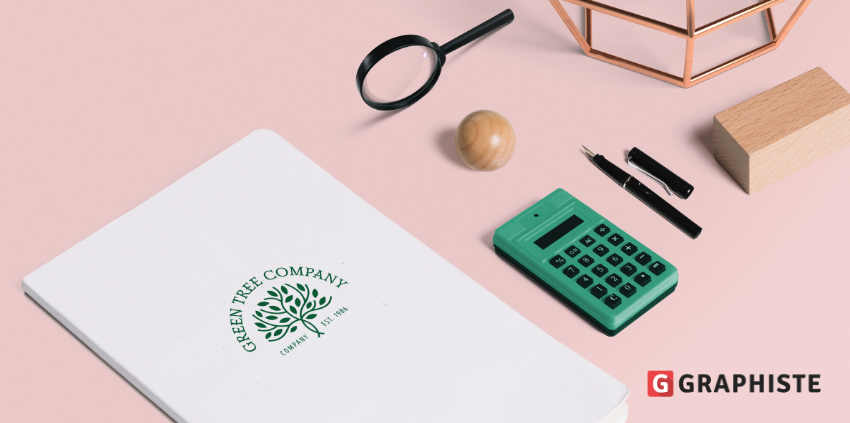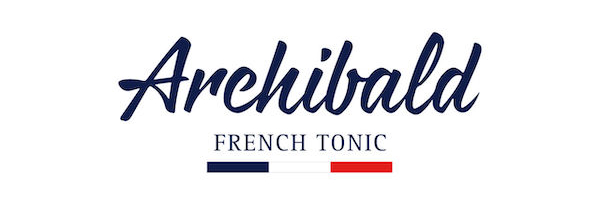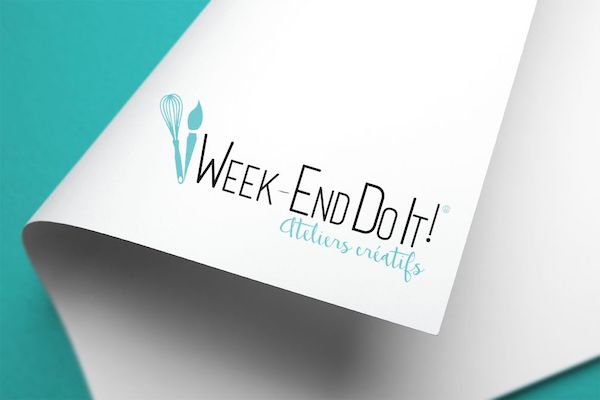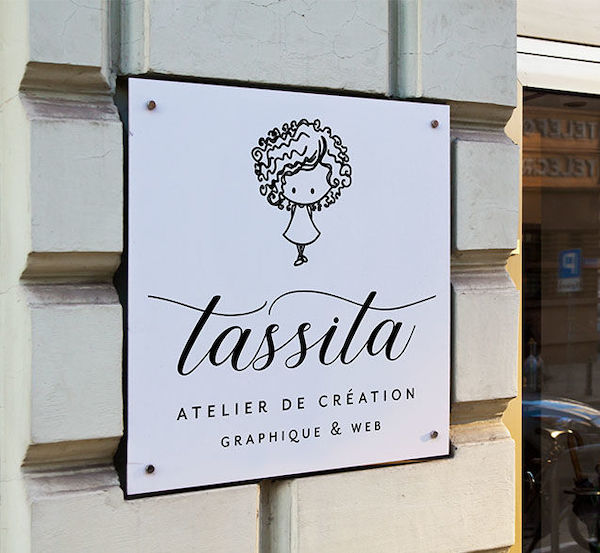
3 conseils pour choisir la typographie pour votre logo
Un logo, c’est une image. Mais c’est aussi une typographie. Que vous optiez pour le monogramme, le slogan ou juste le nom de votre marque, vous aurez souvent des choses à inscrire sur votre logo.
Le choix de la typographie est donc très important : non, le Times New Roman n’est pas une option.
De manière générale, d’ailleurs, il est fort possible que les polices de caractère déjà installées sur votre ordinateur ne correspondent pas à vos besoins.
Pourquoi et comment trouver la bonne ? Lisez la suite pour le savoir !
Votre logo doit séduire un public bien particulier. Si vous vendez des produits d’assurance, vous ne vous adresserez pas aux mêmes personnes que si vous commercialisez des lacets fluo !
Vous devez déjà avoir choisi vos couleurs en fonction de ces cibles. Et vous devez effectuer la même réflexion en ce qui concerne la typographie. Certaines polices seront plus modernes, d’autres plus sérieuses, ou fantaisistes…
Vous devez réfléchir à ce que votre public a l’habitude de voir, à ce qu’il aime, à ses codes. Sans nécessairement imiter ce que font les autres (copier, c’est mal), vous aurez déjà des pistes du type de typographie à retenir.
Songez que votre logo va apparaître dans de nombreuses circonstances.
Sur vos produits, bien sûr, mais aussi sur vos courriers (bonjour le noir et blanc), sur votre site internet, sur des affichages très grands et sur des cartes de visite toutes petites. Dans toutes ces situations, il doit être reconnaissable. Et lisible.
Testez votre typographie pour savoir si toutes les lettres sont reconnaissables, sans nécessiter trop d’efforts, quelle que soit leur taille. Il doit avoir autant d’allure qu’il soit gigantesque ou minuscule. Si ce n’est pas le cas, changez-le. La lisibilité est essentielle.
Pour certains logos, vous aurez à marier deux typographies. Notamment si vous indiquez le nom de votre marque et votre slogan. Et c’est souvent là que les choses se compliquent.
Deux polices de caractère qui ne s’accordent pas, c’est le clash assuré. Visuellement, chacune tentera de prendre plus d’importance que l’autre. L’harmonie ne sera pas au rendez-vous et personne n’aura envie de rester trop longtemps en leur présence.
Vous pouvez éviter cette union ratée de différentes manières. Soit en testant des associations de police déjà existantes, avec des générateurs comme Fontjoy, Fontpair, ou Typ.io. Soit en testant des combinaisons.
De manière générale, les typographies à utiliser ensemble ne doivent pas être trop similaires (sinon la différence est perçue sans être identifiée, créant un sentiment d’étrangeté malvenu), tout en ayant des points communs (même si c’est juste la hauteur des lettres).
Si vous avez juste à créer un logo, le vôtre, vous n’aurez peut-être pas besoin de garder sous la main une collection de polices différentes. Par contre, votre graphiste, lui, vous proposera sans doute un book dans lequel vous effectuerez votre choix. Il pourra même dessiner une typographie qui sera entièrement personnelle, juste pour votre entreprise.
Si vous avez respecté les conseils précédents, le résultat sera à la hauteur de vos ambitions.